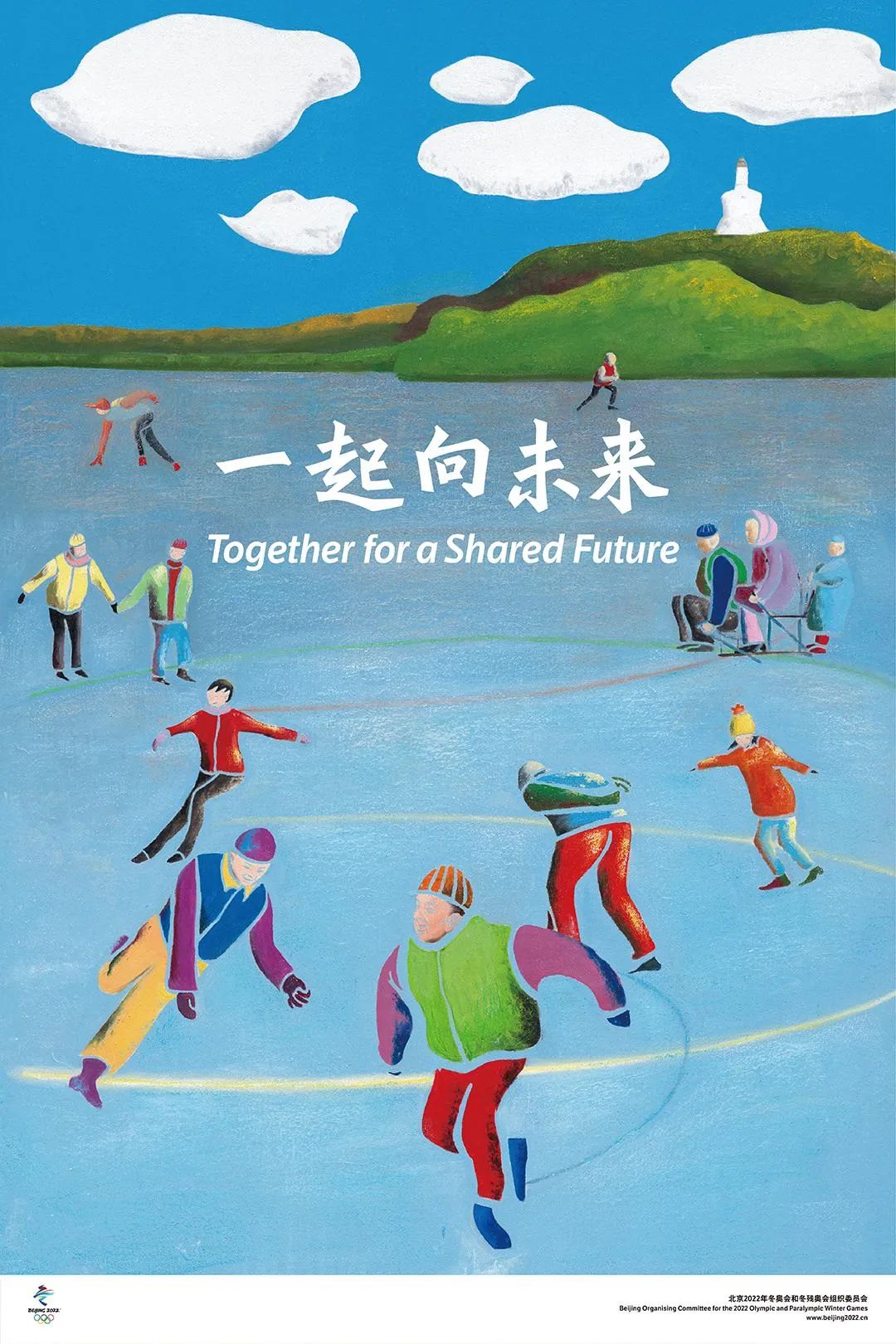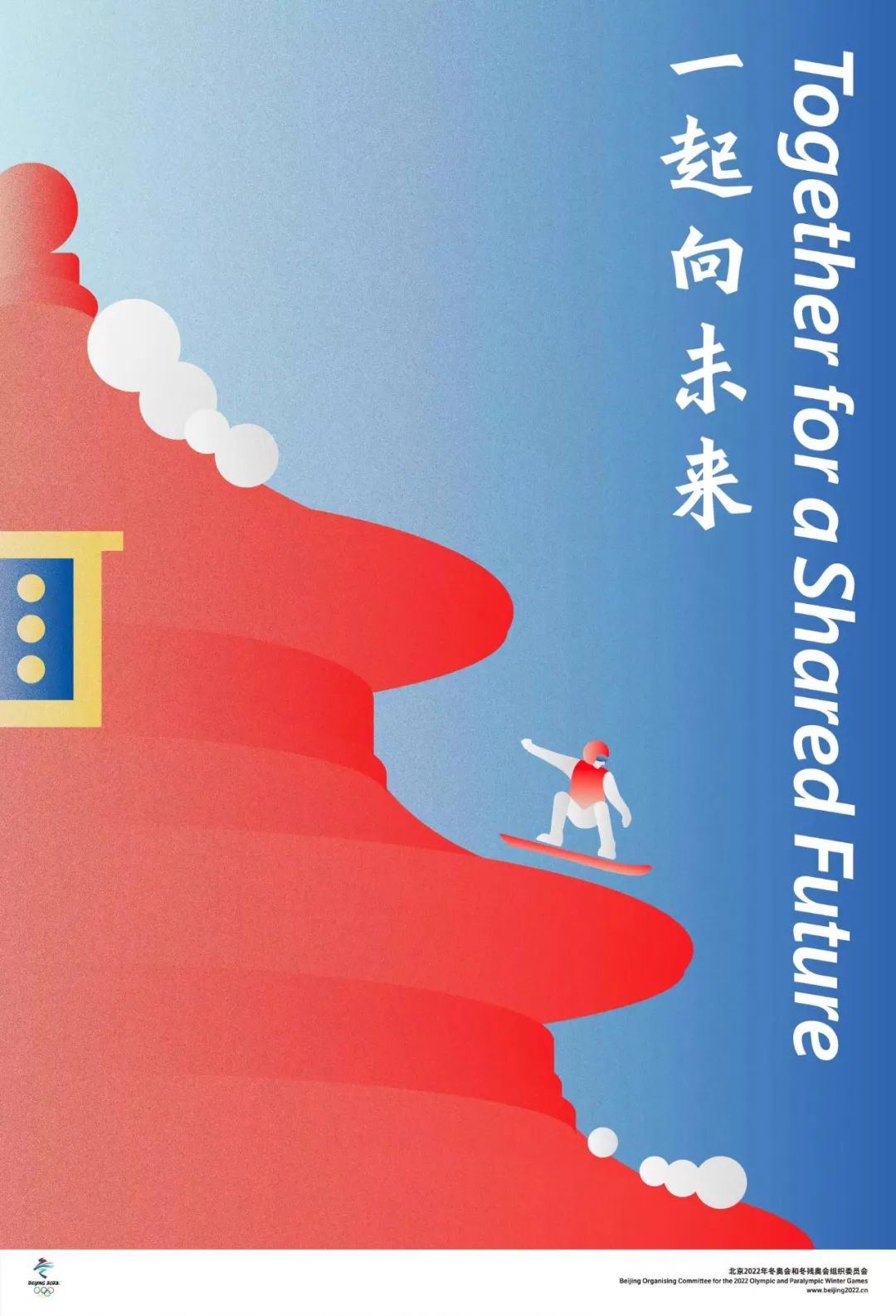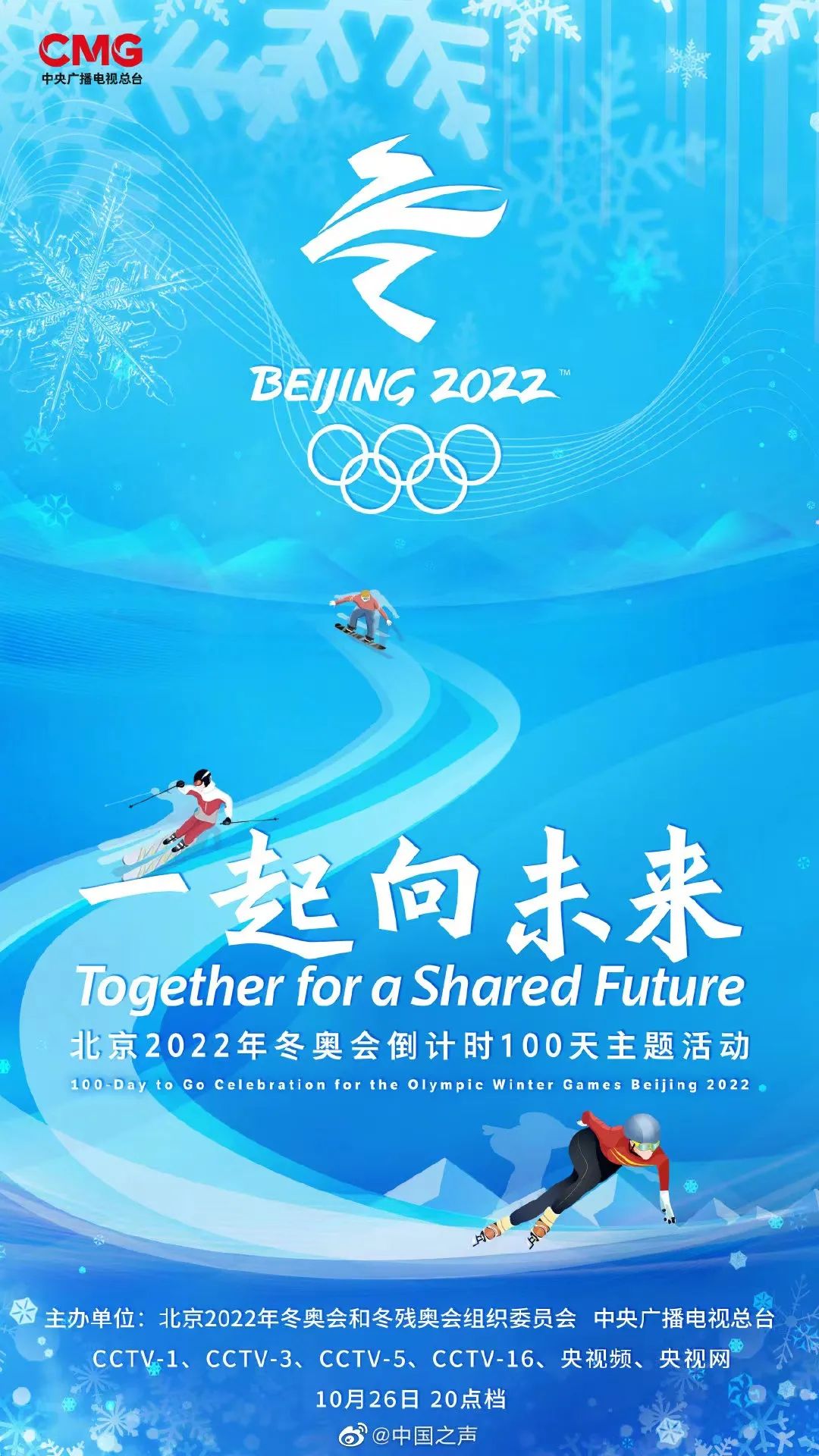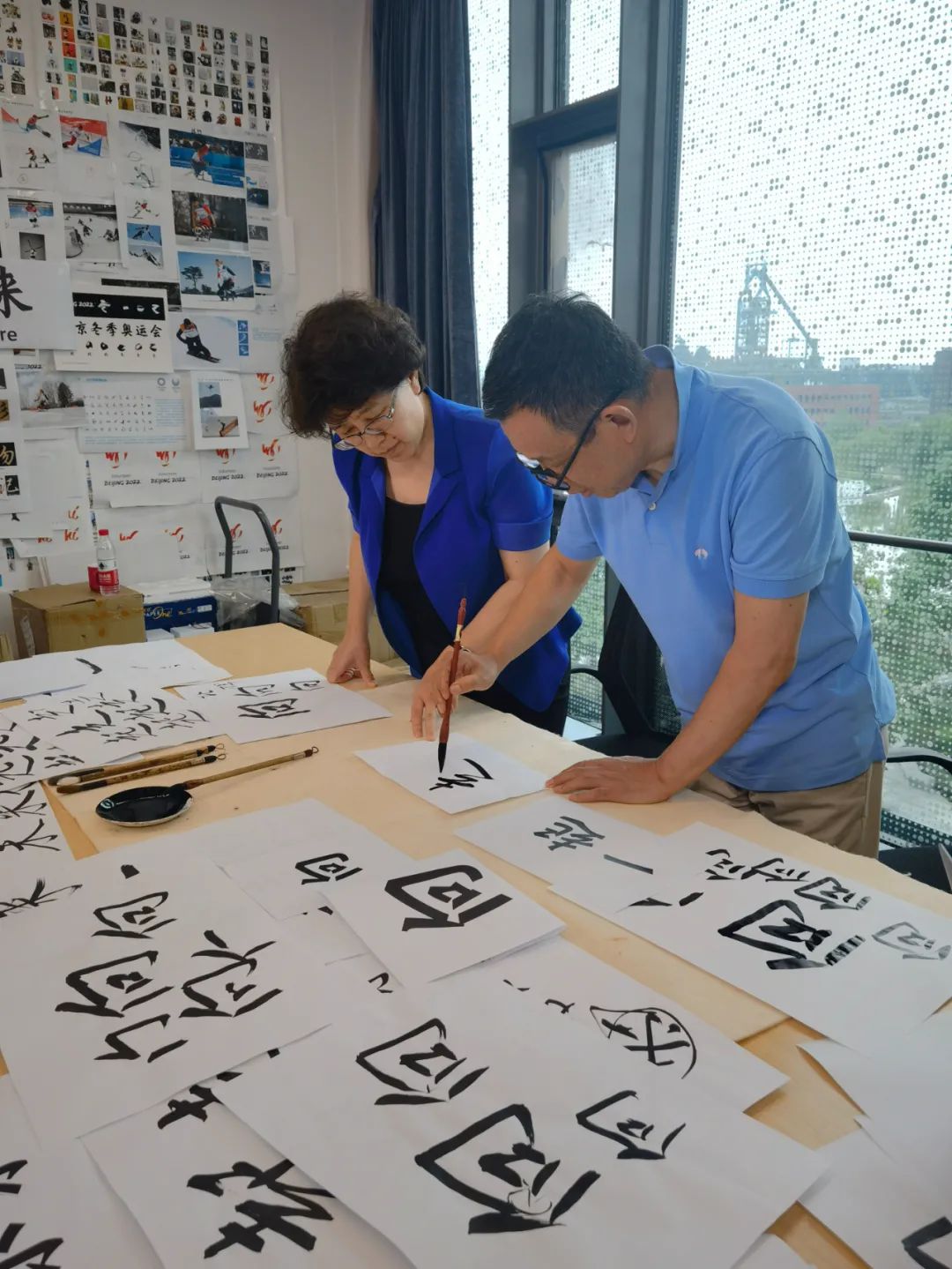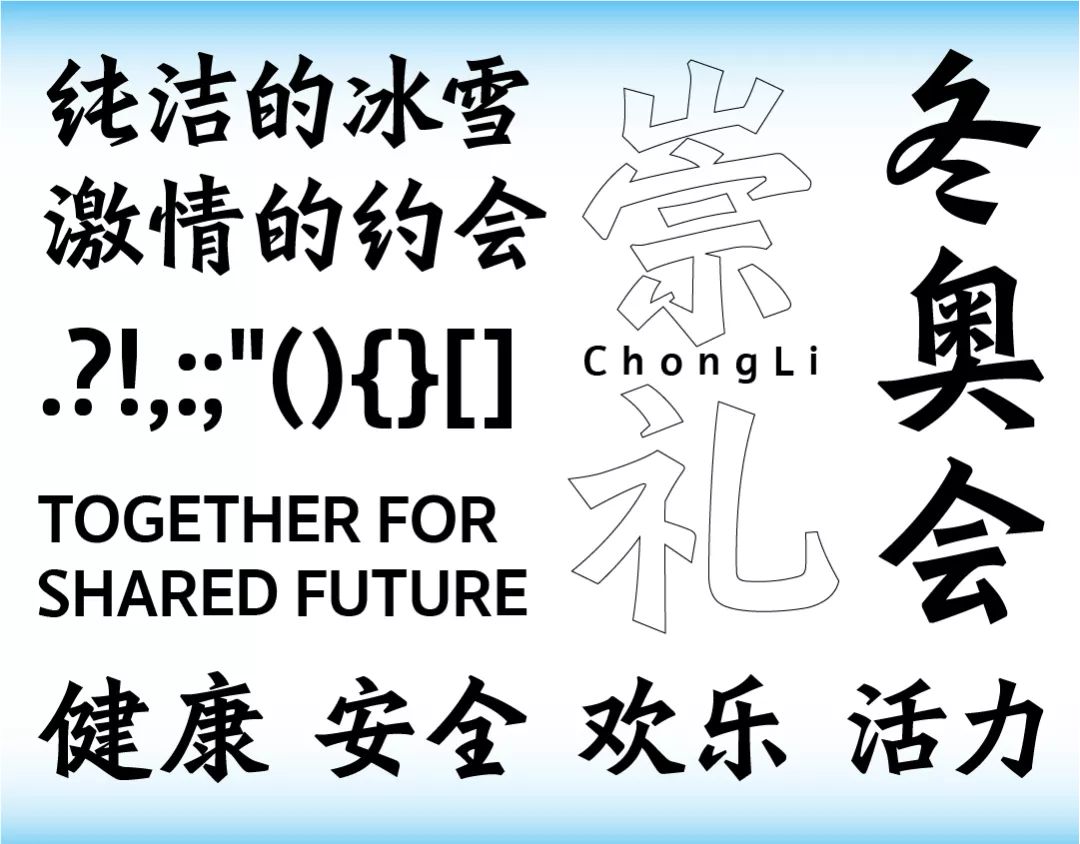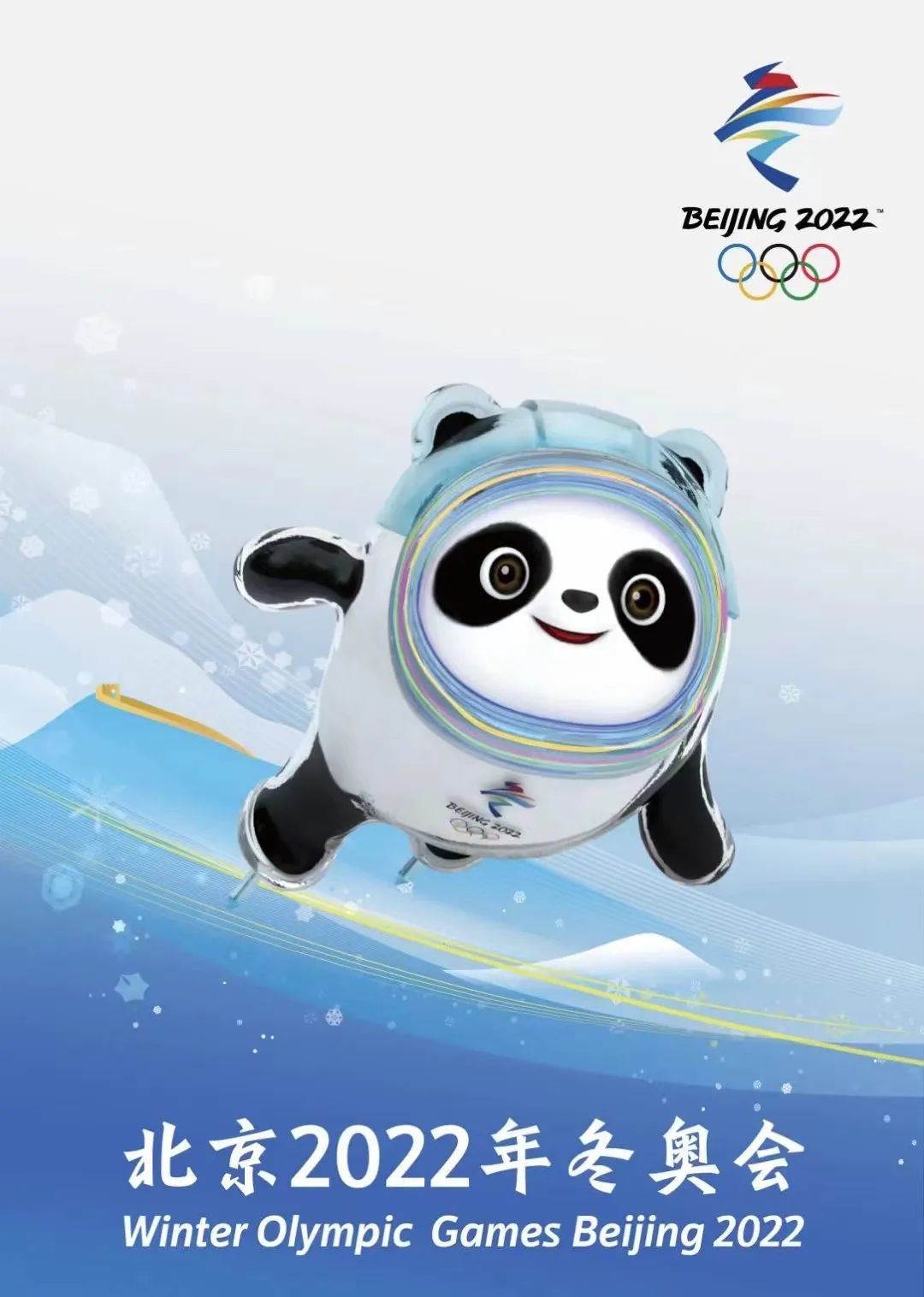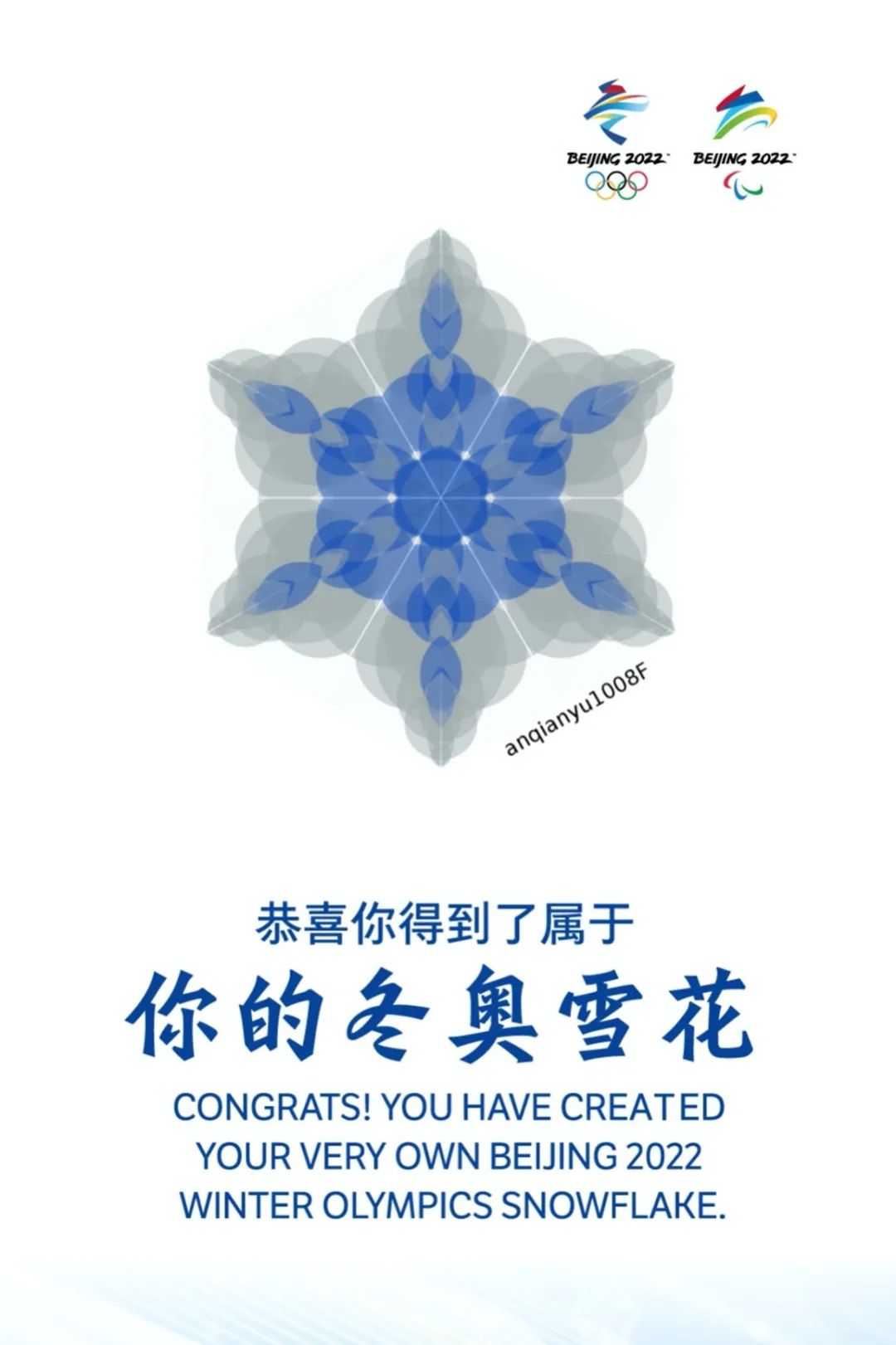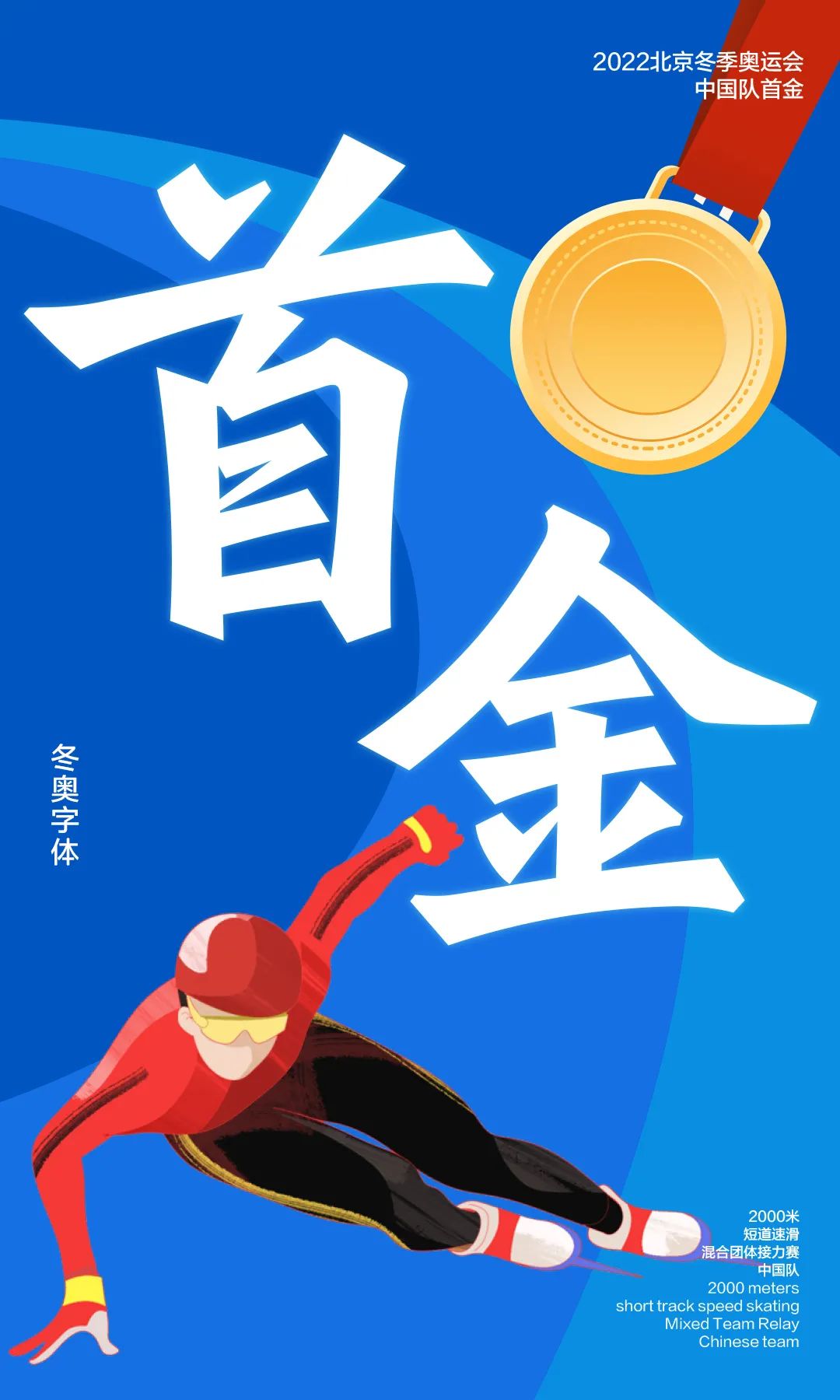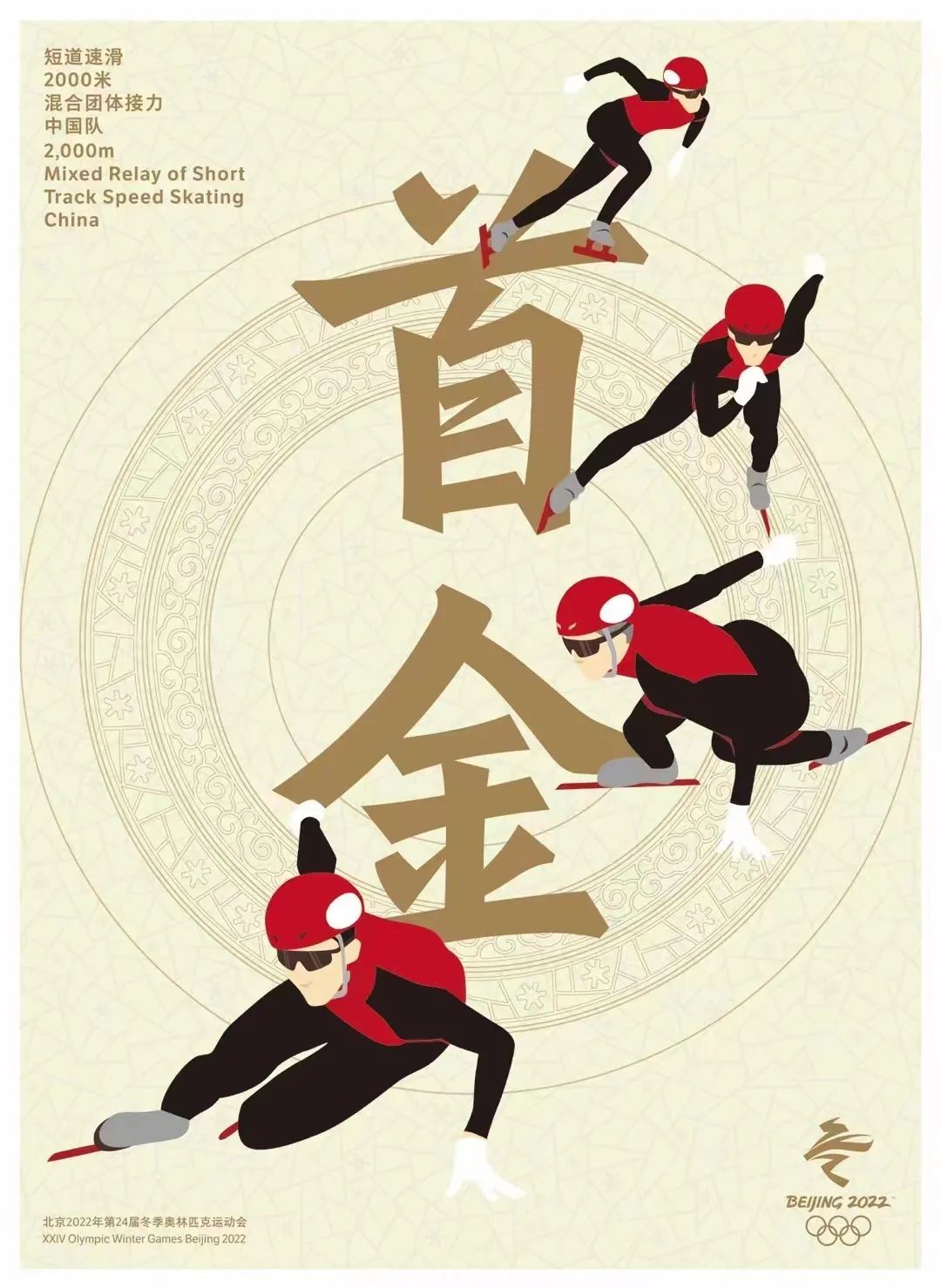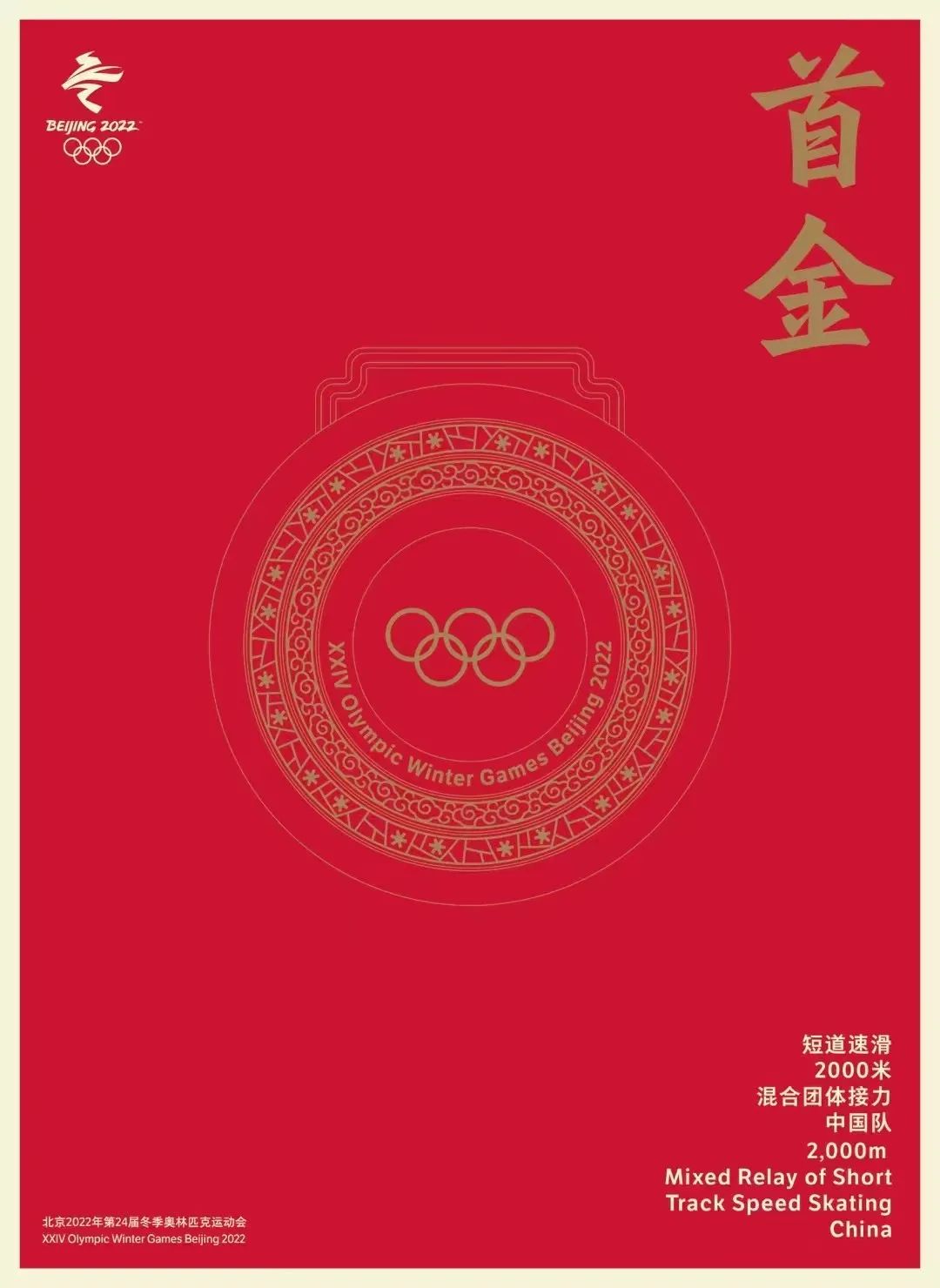
中央美术学院与北京大学合作设计北京冬奥会、冬残奥会专用字体
2022年2月4日晚,举世瞩目的北京第二十四届冬季奥林匹克运动会(下称北京冬奥会)开幕式在国家体育场隆重举行。中华文明与奥林匹克运动再度携手,奏响人类团结、和平、友谊的华美乐章。
近日来伴随着北京冬奥的临近和盛大开幕,火炬传递、比赛场馆、市区街道、各种媒体不断展示着北京冬奥的视觉形象景观全貌,洋溢着既传统又现代的中国文化形象和奥林匹克体育精神。
北京城市、奥运场馆和相关活动的冬奥视觉景观
中华文化源远流长,汉字是最具有代表性的文化符号。北京2022年冬奥会和冬残奥会将是举世瞩目的国际盛会,如果此次北京冬奥会设计专用字体,那将是世界奥运历史上首次进行专用汉字设计并衍生为字库,将进一步凸显了中国对本民族文化的重视,彰显了中国的文化特征、文化自信以及开放友好的情怀。2019年8月中央美术学院与北京大学中国文字字体设计与研究中心联合致函北京冬奥组委,志愿为北京冬奥会和冬残奥会设计开发一套专用字体。冬奥组委复函正式委托了工作任务并对设计工作表示大力的支持。
2021年9月17日,北京2022年冬奥会和冬残奥会主题口号正式对外发布——“一起向未来”(“Together for a Shared Future”),在此次发布会上冬奥会设计专用字体也首次亮相。北京冬奥组委表示,这是中国向世界发出的诚挚邀约,传递出14亿中国人民的美好期待:在奥林匹克精神的感召下,与世界人民携手共进、守望相助、共创美好未来。以冬奥口号——“一起向未来”为代表的专用汉字设计成为了营造北京冬奥氛围的重要元素,成为本届冬奥会视觉形象景观的特色之一。
北京冬奥会主题口号发布仪式现场
北京冬奥会主题口号
北京冬奥会主题口号发布仪式现场创作团队部分成员
北京冬奥会主题口号宣传海报
北京冬奥会主题口号宣传片
北京冬奥会主题口号街头宣传
北京冬奥会主题口号倒计时海报
齐心协力  周密推进
北京冬奥会专用字体设计项目启动之后,中央美术设计学院将专用字体设计创作任务作为视觉传达专业的重要课程进行教学安排,成立了以杭海教授、王子源教授、刘钊副教授以及北京大学中国文字字体设计与研究中心的方正字库专家仇寅老师、汪文老师及TypeTogether字体设计公司总监José Scaglione、Veronika Burian为核心的专项科研教学小组,同时特邀北京冬奥组委文化 活动部形象景观艺术总监林存真教授、刘彦湖教授、周博副教授和彭笑贤讲师进行专门的知识讲座。课程结束后学生阳涛、唐潮、姜田竺、张晁彬、叶昂飞、胡阿提·吾兰、李若一、骆淦、陈一玮、鞠文悦、郝益萱等继续参加奥运专用汉字及拉丁文的深化创作。项目从2019年9月开始,创作周期历时将近2年,主要经历了两个阶段:
在中央美术学院设计学院进行的专用字体课程结课后的全体师生,2019年
第一阶段是汉字研究及方案设计阶段,教学团队按照从“临写到设计”的字体设计方法,邀请了相关专家学者分别做了传统书法与近代字体设计的学术讲座,之后安排学生进行经典碑帖的临写训练,并开始进行冬奥专用汉字字体的设计。北京大学中国文字字体设计与研究中心方正字库的专家也参与了具体的教学指导;同时承担起汉字专用字体字库的准备、调整与制作工作。
字体课程受邀专家教授讲座及指导老师们授课现场,2019年
课程第二阶段,团队分成汉字与拉丁文两个工作小组:为了让拉丁文设计体现出国际化的专业水准,项目组特别邀请国际著名的字体设计公司TypeTogether的设计总监、国际字体协会前任主席José Scaglione来华进行拉丁文字体设计指导,之后定期与TypeTogether公司专家进行远程沟通,初步建立冬奥会专用拉丁文字体风格,方正字库的导师也全程参与指导与修改工作。
北京冬奥会专用字体拉丁文授课现场,2019年
以字为礼  衷心呈献
在中央美术学院设计学院以研究带动项目的教学、科研开启了冬奥专用字体设计的新模式。团队认识到北京2022年冬奥会会徽视觉主体为行楷风格设计的“冬”字受到广泛关注与好评,根据奥运形象景观设计的统一原则,项目团队用心体会会徽风格的笔意,并溯源从中国书法当中研究和提炼,与会徽图形结构相结合,在总体概念上延用书法的行楷结构、以王羲之书法特征等为设计灵感与结构基础,从而形成多款新的艺术字体设计方案。同时配合相应的拉丁文设计,以体现冬奥会所特有的运动、激情、速度与韵律。
汉字也是整体的艺术,新的设计方案在汉字的点画、结构、行气中努力让古老汉字以新的当代风格传递中国汉字文化与审美,注重打造具有中国特色的冬奥运动形象景观,为世界奥林匹克文化增加中国汉字艺术的文化遗产。设计团队在之后在长达一年的时间里与冬奥组委文化活动部进行多次沟通并根据反馈意见和赛事实际需求进行深化设计,最终确认了两套字体报北京奥组委审阅。
北京冬奥会专用中文字体创作手稿
北京冬奥会专用中文字体过程方案一
北京冬奥会专用中文字体过程方案二
筑梦冰雪  精益求精
冬奥组委大力支持专用字体设计工作,2021年7月征求了多方专家意见确认了延续北京冬奥会会徽及书法行楷风格的设计方案总体方向。同时在设计方案的最终修改阶段也邀请中央美术学院刘彦湖教授指导,对文字的笔画走向、起笔收笔等细节处进行了修改。之后也请中国书法家协会副主席、首都师范大学叶培贵教授进行指导,在风格上有了进一步的调整,倾向于行楷与魏碑的结合,笔画更加锐利、敦厚,呈现力量感。在起笔、收笔和运笔的过程中,也融合魏碑的风格,凸显刀刻的感觉和笔画阴阳向背的变化。字体整体收腰,撇捺舒展、重心略高,更加充满力量感与精气神。
同时拉丁字体进入最后修改阶段,在方正字库专家汪文的指导下,拉丁文字设计上增添了书写特征,强调了笔画的粗细对比,使笔画有流畅的手写感觉;此款字体笔画细节处理上较为简洁,流畅性和平整度都较为凸显,整体感较强,且更加亲切和彰显国际化。
中央美术学院刘彦湖教授提供字体指导建议
首都师范大学叶培贵教授提供字体指导建议
北京冬奥会专用字体专家组部分成员及北京冬奥组委文化活动部专家研讨字体最终设计方案修改
北京冬奥会专用字体字形展示
花开万树  同心而行
北京冬奥会专用字体让古老的汉字艺术以现代容貌活跃于民族文化之林;将冬奥文化深深根植在人民群众的生活中,成为人们沟通彼此、联系世界的重要媒介;通过打造具有中国特色的冬奥形象景观,为世界奥林匹克文化再次增添中国文化特色,体现中国的文化自信。一撇一捺,都是汉字书写者衷心呈献给北京冬奥的一份礼物。专用字体广泛应用于冬奥形象传播中,如场馆、火炬传递、海报及电子媒介中。
北京冬奥会专用字体实际应用展示
助力冬奥  共向未来
在奥运会开幕式中,各代表团入场是必备环节,这一环节中引导牌等细节设计往往也能凸显举办国的文化特色。北京冬奥会开幕式入场引导牌采用中国结流线型组成的雪花形状,引导牌上亮起的代表团名称字体,经中国文字字体设计与研究中心的字体专家试验不同字体,并向张艺谋总导演汇报呈现效果,最后选择在方正魏碑字体的基础上进行再设计。由于引导牌是发光装置,在拍摄和电视转播时会形成光晕,所以字体要求较传统魏碑字体减细。通过中国文字字体设计与研究中心的字体专家和道具制作单位的反复实验,最后定为减细20%。
中文字体在引导牌上的尺寸在6-10厘米之间,由于发光管的技术要求,字形最细的地方不能小于3毫米。字体设计师们不断调整字体笔画的粗细,将细的部位加粗,将特粗的部位减细。最后呈现的字体结构合理,笔画粗细更加均匀。体现出魏碑字体端庄厚重、充满力量的中国楷书风貌。
最后的点燃主火炬环节,所有参赛代表团的文字引导牌汇聚成主火炬的大雪花造型。让文字承载着所有奥运健儿的愿望,充分体现出更高、更快、更强、更团结的奥运理念。
汉字是中华民族的文化代表,也是人类世界共同的精神财富。北京冬奥会专用字体旨在传承中华优秀传统文化,弘扬中华汉字书写精神,通过将汉字艺术与体育运动中的力量、气势等审美特质融为一体,以汉字书写诠释对冬奥精神内涵的理解,向全世界展示中国的体育精神、文化魅力,展现自然之美、人文之美与运动之美。
北京冬奥会专用字体设计团队
中央美术学院设计学院
北京大学中国文字字体设计与研究中心